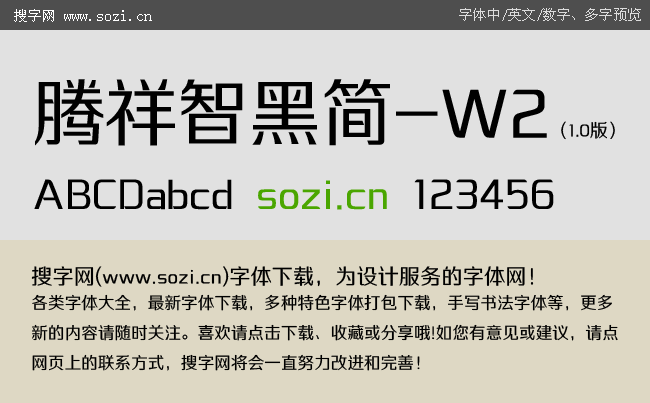
騰祥智黑簡-W2
搜字網(wǎng)提供一款非常藝術(shù)的黑體字騰祥智黑簡-W2下載,騰祥智黑是騰祥睿黑的姊妹篇,風(fēng)格相近但排版效果迥異,騰祥智黑與騰祥睿黑的差別在于更加強調(diào)了黑體的特征,筆畫簡潔、硬朗更穩(wěn)重大方;字形結(jié)構(gòu)方正、端莊,橫豎筆畫挺拔,軟筆畫細(xì)膩、柔美。點形到撇、捺形都做了大膽的創(chuàng)新,塔形頓點、撇點賦予了智黑特殊的設(shè)計效果,富于設(shè)計感,適用于包裝印刷、廣告設(shè)計、平面設(shè)計、書籍報紙等領(lǐng)域。